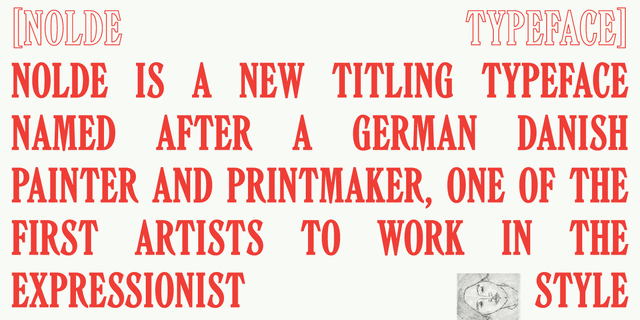
Шрифт назван в честь Эмиля Нольде — немецко-датского художника, одного из первых экспрессионистов: за спокойным ритмом букв скрывается драматизм форм и нервность линий. Рисунок Нольде отсылает к металлическим шрифтам первой половины двадцатого века, но его образ свеж и современен, что позволяет шрифту идеально работать в остроактуальной акциденции. Гарнитура включает в себя два начертания: обычное и контурное; состоит из прописных знаков и поддерживает множество языков, использующих латинскую и кириллическую письменности. Дизайнеры Вячеслав Кириленко и Гаянэ Багдасарян, 2015.